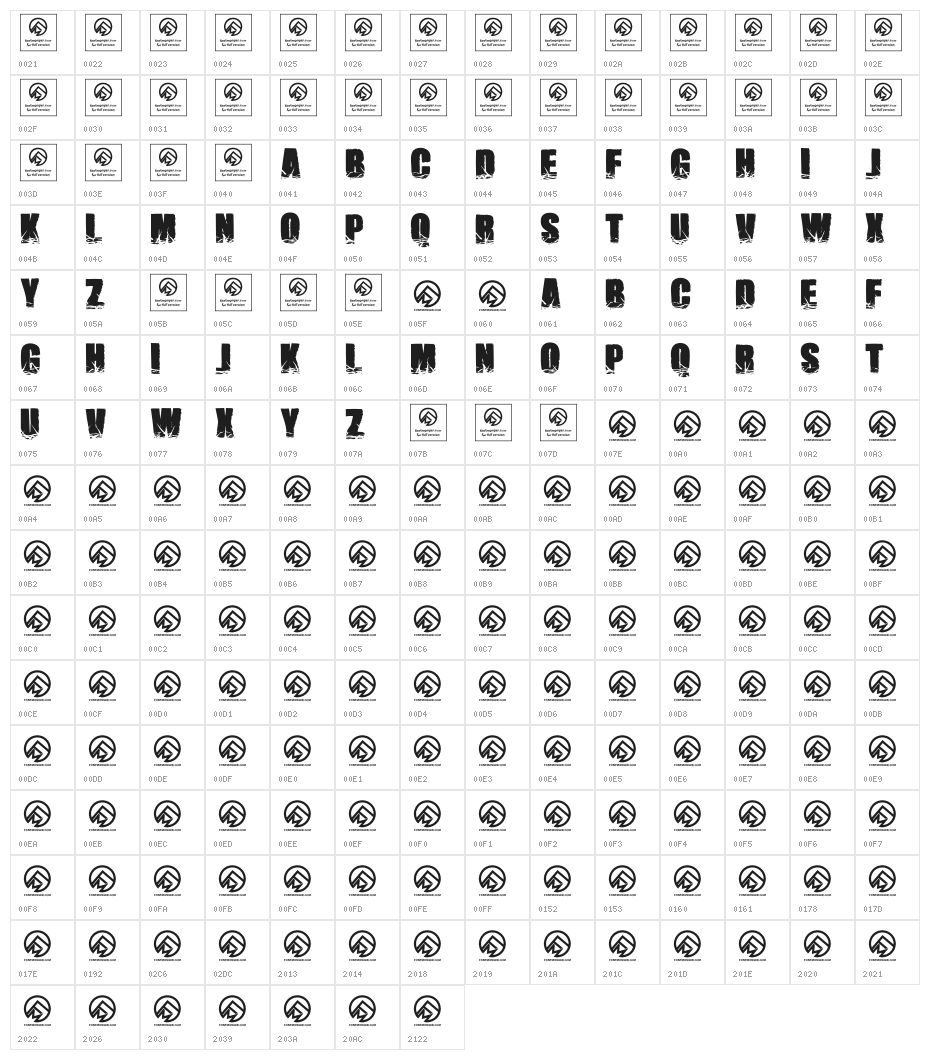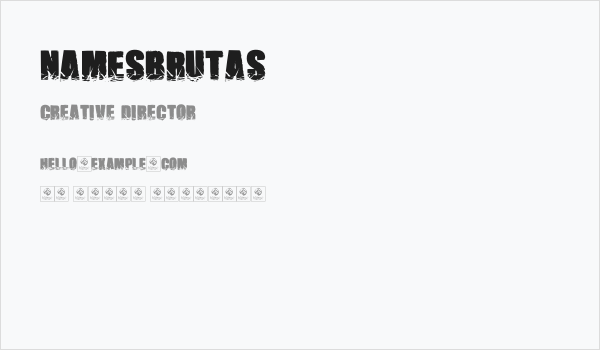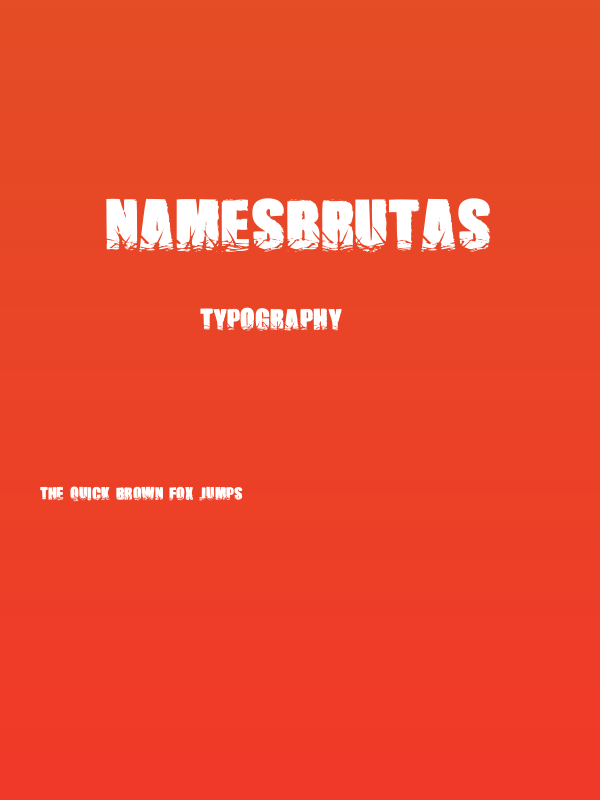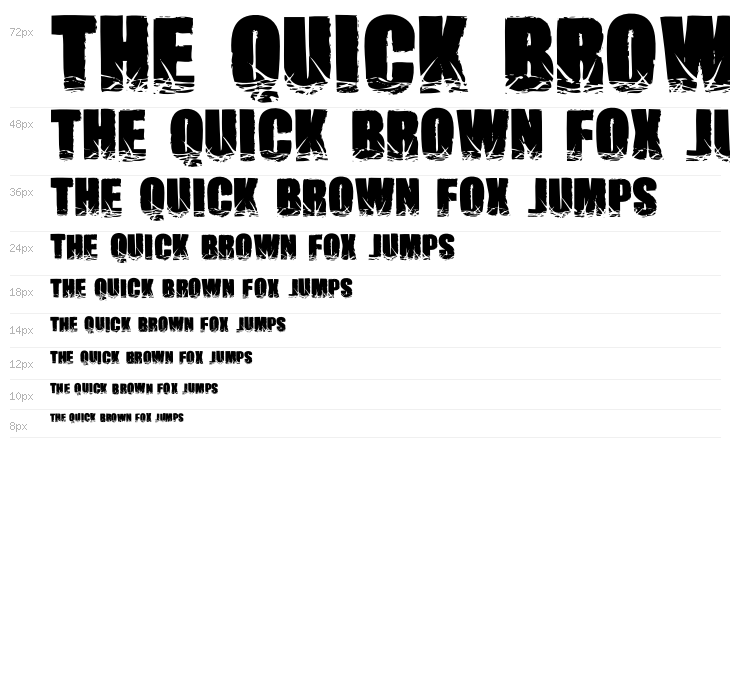
NamesBrutas Font
✎ Thick
| श्रेणियाँ | Thick |
| कंट्रास्ट | High |
| समग्र शैली | Decorative |
| उपयोग का मामला | Headlines, Logos, Posters |
| सुझाए गए प्रोजेक्ट | Ideal for posters, album covers, branding for extreme sports, or any project needing a bold, edgy look. |